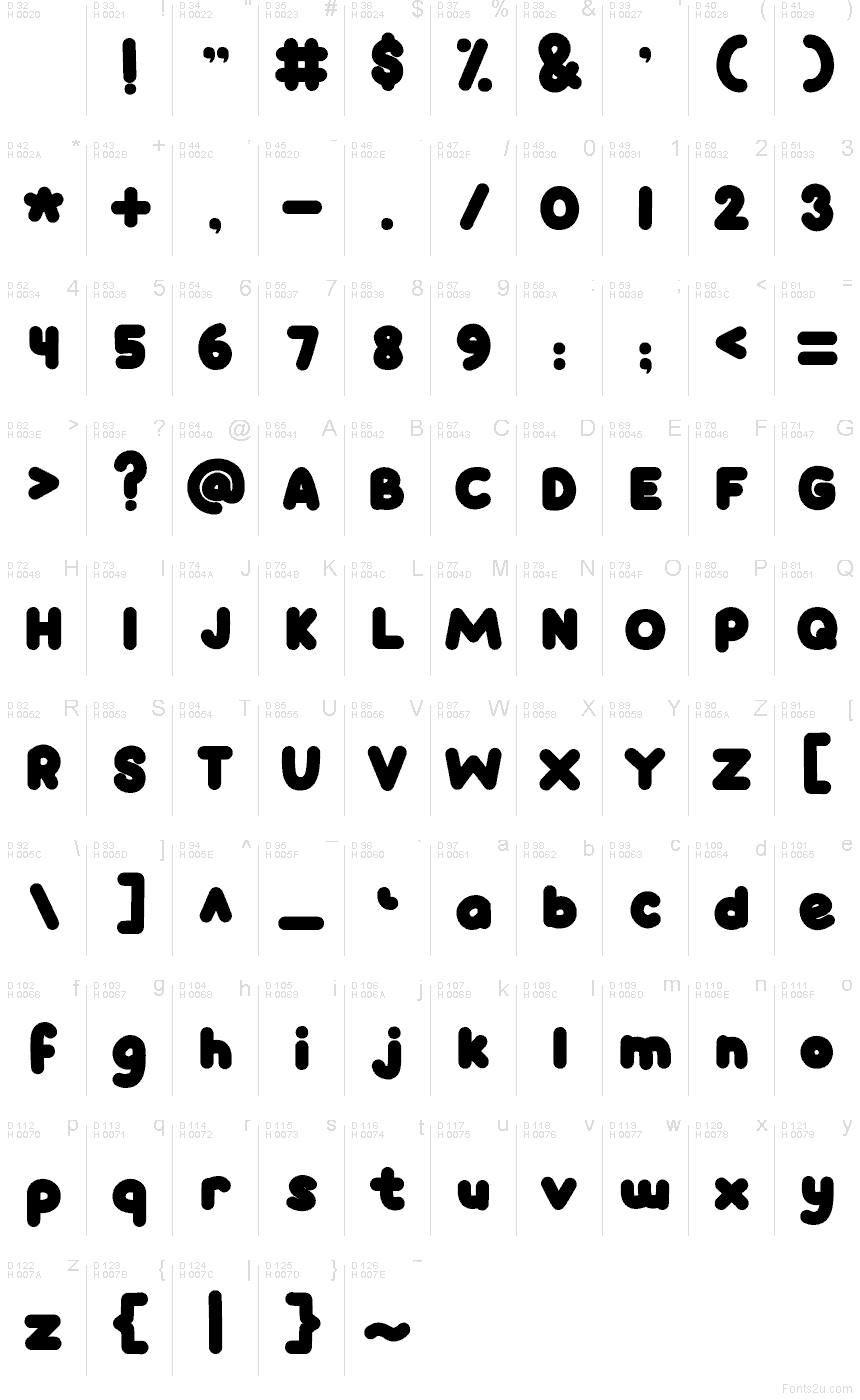
BUNDEL
Bundel od Tokokoo je bezplatné kreslené písmo typu display s veľkými, nadýchanými veľkými písmenami a mäkkým, skákavým rytmom. Písmená pôsobia nafúknuto a priateľsky, majú hrubé zaoblené tvary, tesné spoje a výrazné zárezy, vďaka ktorým je abeceda veselá a nie príliš uhladená.
Prirodzene zapadne do detského brandingu, na obaly sladkostí, pozvánky na večierky, komiksové nadpisy a veselé plagáty, kde toto bezplatné písmo s veľkou dávkou dynamiky dokáže niesť krátke slová už len svojím tvarom. Použite ho na titulky, úvodné karty alebo výrazné skice log, ak chcete, aby veľké písmená pôsobili mäkko, jednoducho a okamžite optimisticky.